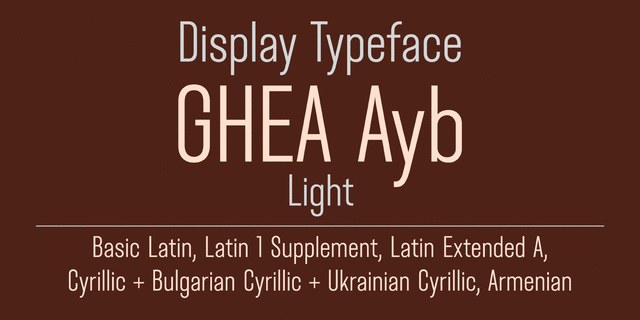
Этот узкий акцидентный гротеск может использоваться в названиях, заголовках и коротких текстах. Ayb поддерживает расширенную латиницу, кириллицу, включая украинские и болгарские варианты букв, а также армянский алфавит. Шрифт разработал Эдик Габузян в 2020 году.